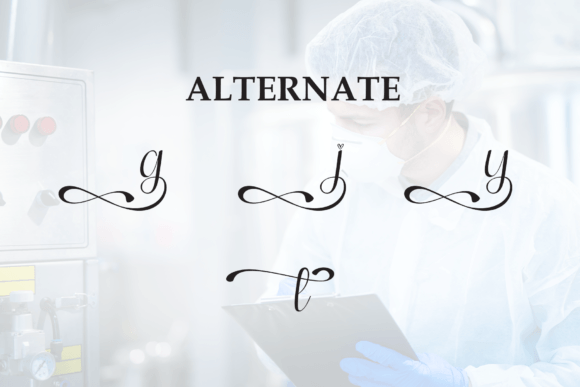
Quality Font
منتج “خط الجودة” هو تصميم رقمي احترافي يوفر لك خطًا أنيقًا ومتميزًا يناسب مجموعة واسعة من المشاريع. يتميز هذا الخط بوضوحه ومرونته، مما يجعله مثاليًا للاستخدام في الشعارات، بطاقات الدعوة، والمطبوعات الإبداعية. سهل الاستخدام، يضيف لمسة من الأناقة والاحترافية إلى أعمالك، ويساعدك على التعبير عن هويتك بشكل مميز!